传承古老文化,弘扬书法艺术
--记汉呈安景臣行书繁字体的书写者安景臣
安景臣先生
书法艺术,是中国特有的文化艺术,在中华文明的历史长河中扮演着重要的角色,它记载着华夏文明、它发展了艺术审美,留下了众多价值连城的佳作,涌现出诸多艺术家,使得中国古老文化熠熠生辉、璀璨夺目。
汉呈安景臣行书繁字体欣赏
而到了近代、当代,却很少有人注重书法艺术了,尤其是电脑的普及,许多人提笔忘字,也很少用笔写字了,更谈不上用毛笔写字了,因此,现在书法艺术备受冷落,传承受到了危机。如何才能将这一古老文化继承和发展,是摆在我们面前的非常重要的课题。
安景臣先生的国瓷作品欣赏
自从有了电脑,人们用字,几乎都是在电脑里调用。电脑里的书法字体这几年也逐渐地多了起来。字体一般是有版权的,但是除了少数大公司可以付费购买以外,对大多数个人使用都是免费的。这给人们日常应用带来了极大的便利。但是,由于现在提倡简化字,繁体字库少之又少,仅有的繁体字库往往质量不高。看到这一现象,作为研究多年书法艺术的安景臣决定编写一套繁体字库,弥补繁体字库不足的弊端。
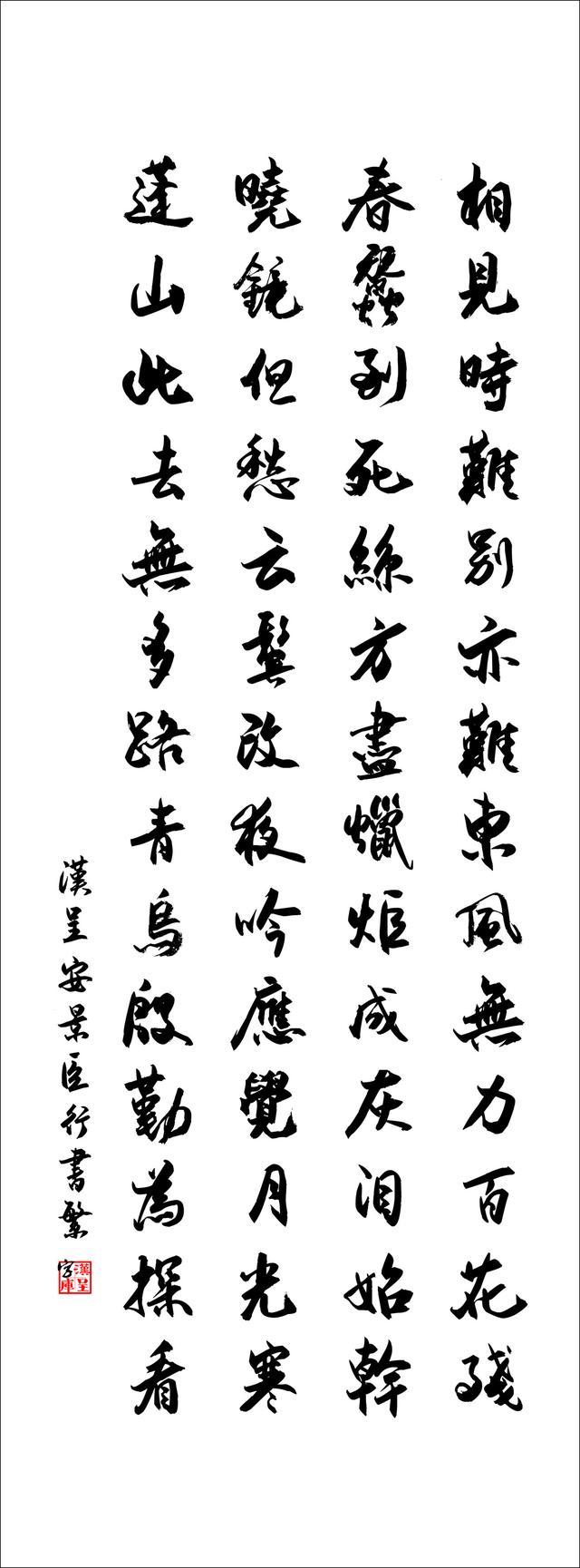
汉呈安景臣行书繁字体欣赏
因为书法艺术是传承古代书法家作品的艺术,因此,直到现在,书写书法作品大多数都用繁体,繁体字有自己独特的美。在日常应用当中,打字也希望打出的字有书法风格,因此,繁体字有一定的市场,然而,由于搞书法的很少有涉及字库行业的,因此,现在的繁体字库少之又少,这是目前电脑用字繁体字库匮乏的主要原因。
安景臣先生书法作品欣赏
而安景臣自幼喜爱书法艺术,对各种字体信手拈来,了如指掌。当汉呈字库的王天喜老师找到他,让他写一套繁体字库时,他愉快地答应了。
安景臣先生书法作品欣赏
由于一套字库有6千多个字,他利用业余时间,每天写一二百字,不到一个月的时间,完成了整套字库的书写任务。他每写一部分,就发给王天喜老师制作一部分,分成四部分书写发送,感觉还是比较轻松的。这源于他多年来积累的书法功底,很少写错字,书写速度也较快。但是,遇到写错过写坏的情况,整页就要重写。王天喜老师说,如果写错了只要把写错的字盖住重写就行,而安景臣是一个精益求精的人,做事讲求完美,一张字稿上那怕有一笔不好他都整张重写。这样,他书写完了整套字库,每个字都力求完美,发布到网上,受到了大家的一致好评!
汉呈安景臣行书繁字体欣赏
安景臣在此之前,曾发布过十余套书法体字库,在电脑端,手机端广受欢迎。他的第一套字体要追溯到十余年前。第一款字体安景臣钢笔行书曾被各大网站转载,广受欢迎!后来又有安景臣硬笔行书,安景臣硬笔楷书相继问世。曾被多家大型企业采用,并选为字帖出版专用字体。后来又有景晨系列字体入驻各大手机平台,安景臣在字体界的知名度越来越大了。
汉呈安景臣行书繁字体欣赏
他的梦想是造更多的字体,造福社会,让书法这一古老文化艺术在网络时代发扬光大,传承中华传统文化、弘扬书法艺术,在网络时代为书法艺术的普及尽心尽力!